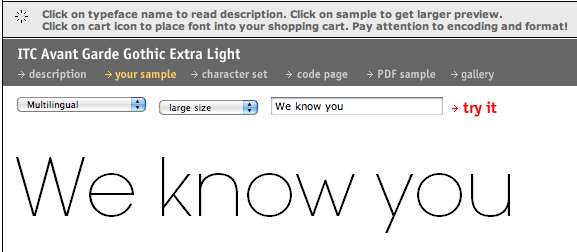
was könnte das wohl sein???
Das ist fast die Helvetica Neue ultra thin, nur die Unterlänge vom y ist unterschiedlich. Hmmm …
Nachtrag: Auch die Gotham Extra Light ist dicht dran, aber bei ihr läuft die Unterlänge des y ebenfalls in einem Bogen aus.
Ich dachte eher an eine Avant Garde, wegen dem t.
Aber da ist wiederum das k anders :-?
Die von URW passt auch fast, das n ist ein wenig breiter.
Warum sollte jemand daran gebastelt haben?
Hans Reichardt hat doch bestätigt, dass es sich um die Avantgarde-Version von Paratype handelt.
Warum sollte jemand daran gebastelt haben? Hans Reichardt hat doch bestätigt, dass es sich um die Avantgarde-Version von Paratype handelt.
Hans Reichardt liegt damit aber leider falsch, da beispielsweise das n auch der Paratype-Fassung breiter ist als im Ausgangspost:
Da wird – wie Kathrin schon vermutet hat – jemand gebastelt haben.
Puh, auf die Diskussion möchte ich mich nicht einlassen, ob die beiden n wirklich unterschiedlich breit sind. Man beachte, dass es sich hier um zwei verschiedene Screenshots handelt, die durchaus an unterschiedlichen Betriebssystemen entstanden sind. Dann der Negativ-/Positiv-Unterschied, die Render-Software von Paratype usw.
Natürlich ist es durchaus möglich, dass an dem n gebastelt wurde. Aber mit der Paratype-Version ist man extrem nah dran. Alles andere ließe sich nur anhand wirklich aussagefähiger Bildgrößen überprüfen.
Es sieht mir so aus als hätten die für das n ein m massakriert … die Breite stimmt jedenfalls mit dem Teil des m überein.
glaub ich nicht, wieso sollten die sich die arbeit machen?
kann ja auch ein billiger avantgarde-klone sein.
Billig? Preiswert? Oder Gleich umsonst? URW GothicL!? Ich finde nur keine XLight ... Oder hat da einer die weiße Schrift mit schwarzer Outline verdünnt? Das wäre auch noch eine Möglichkeit.